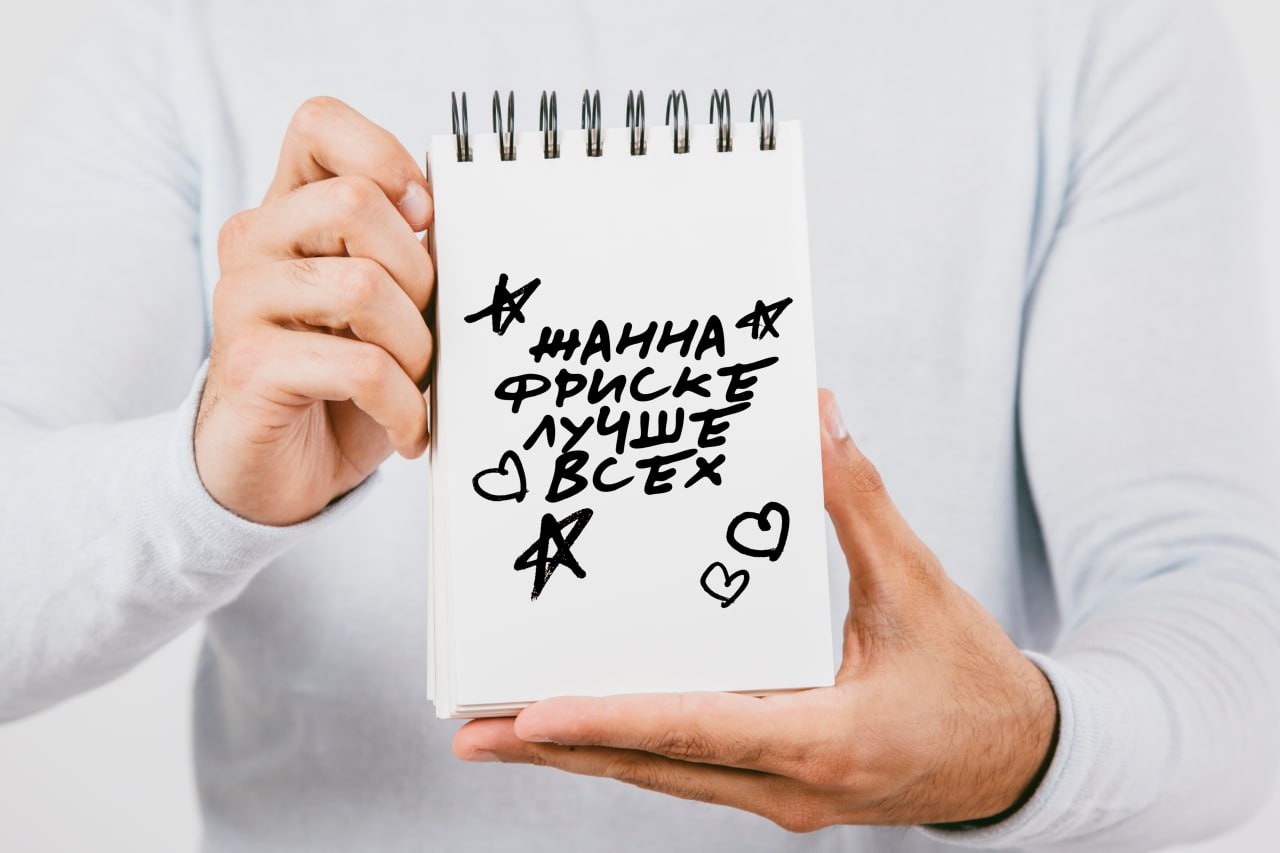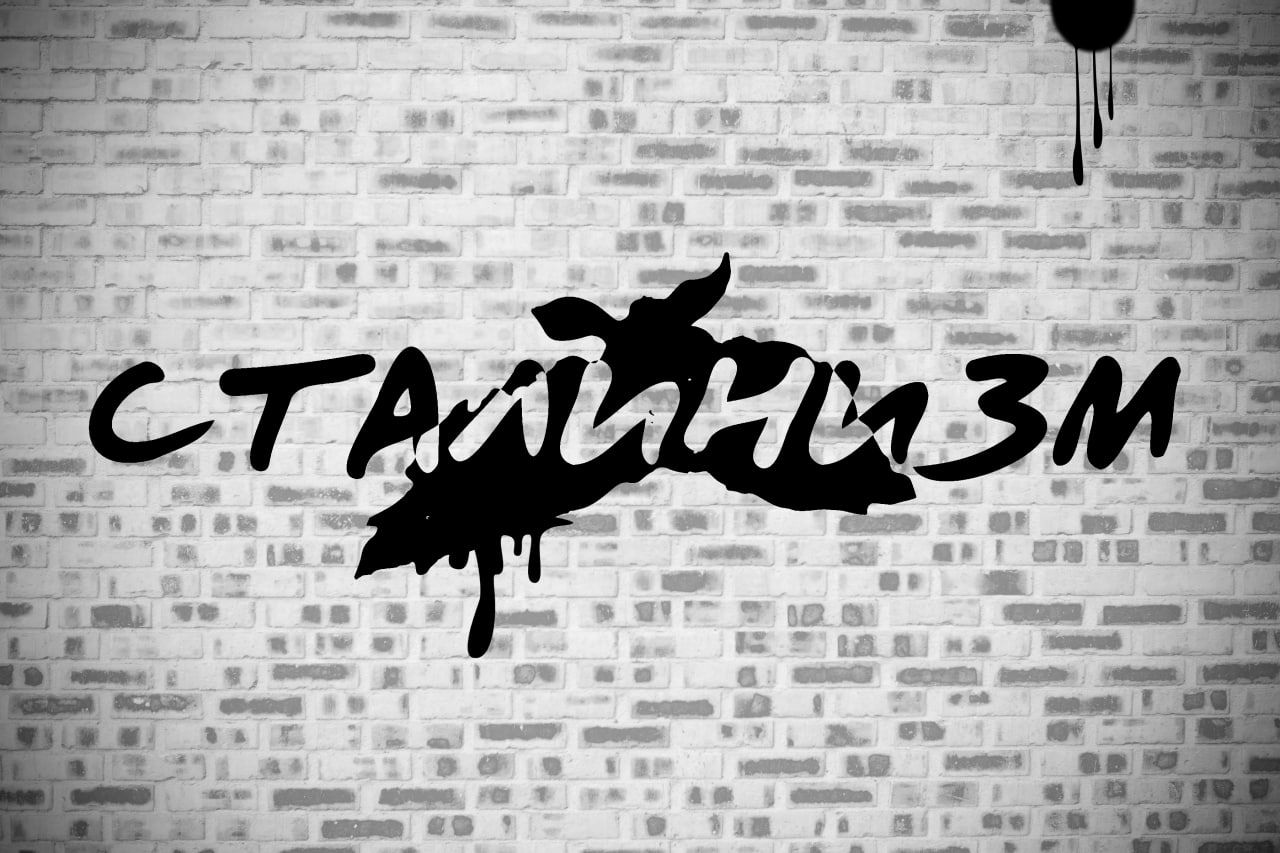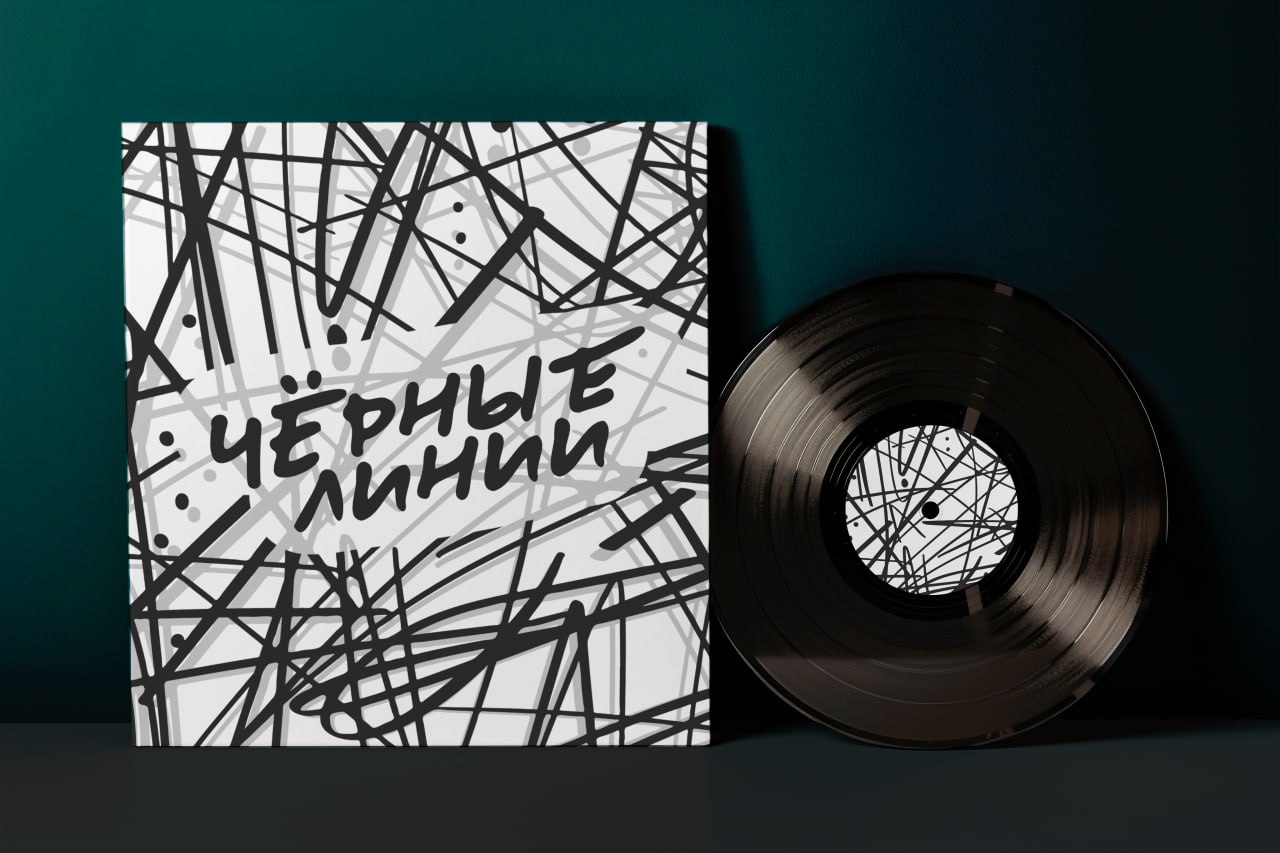
Шрифт Леонов
Leonov — экспрессивный шрифт с плотным маркерным штрихом, крупными формами и заметным наклоном; окончания мягкие, в строке остаётся лёгкая графическая небрежность. Он разработан по мотивам леттеринга с плаката Юрия Леонова «Сталинизм» и сохраняет ощущение быстрой авторской надписи. Хорош в заголовках, на стикерах, в музыкальных визуалах и всём, что тяготеет к неформальной, андеграундной подаче. В комплекте — полная версия STAR и лицензия.